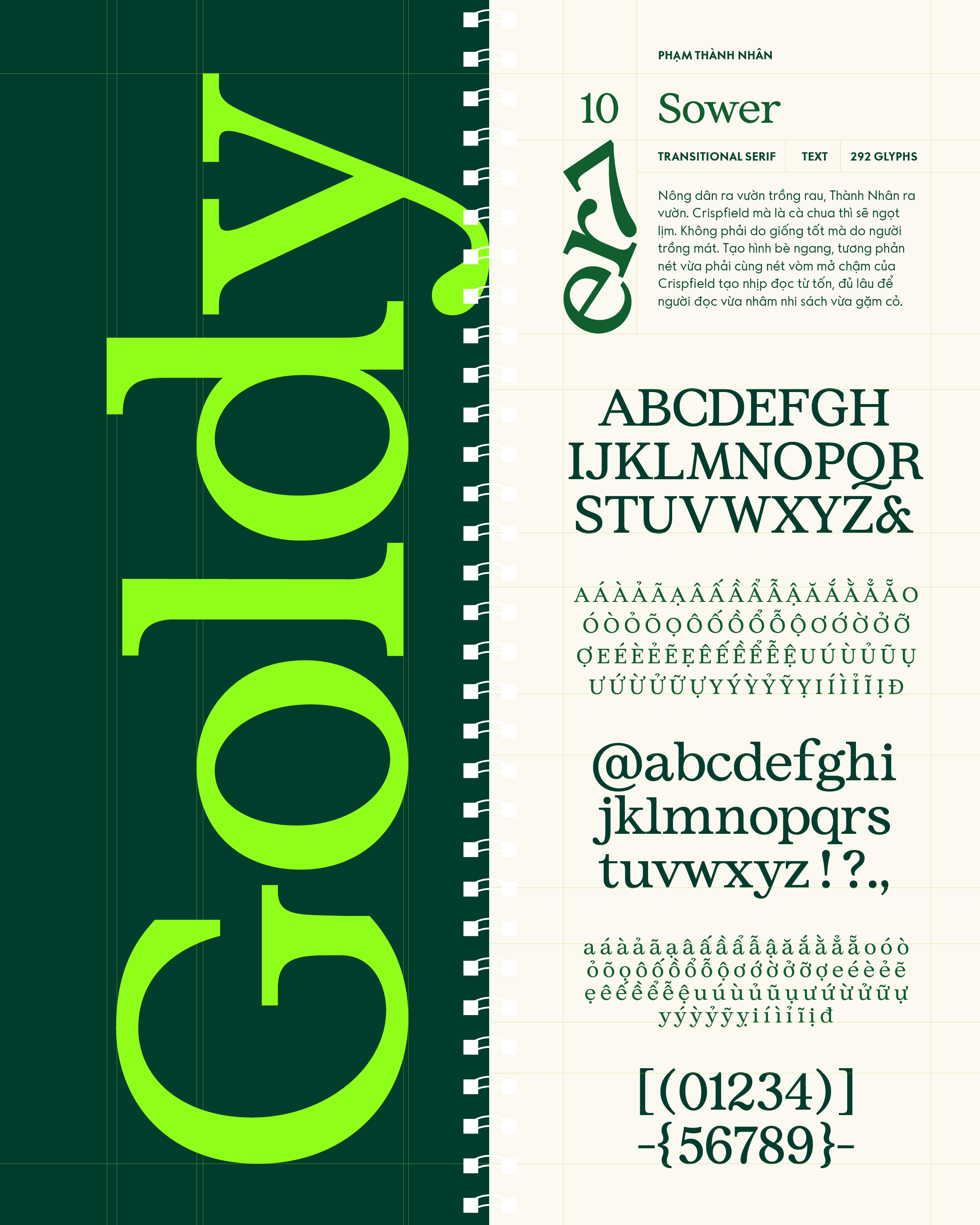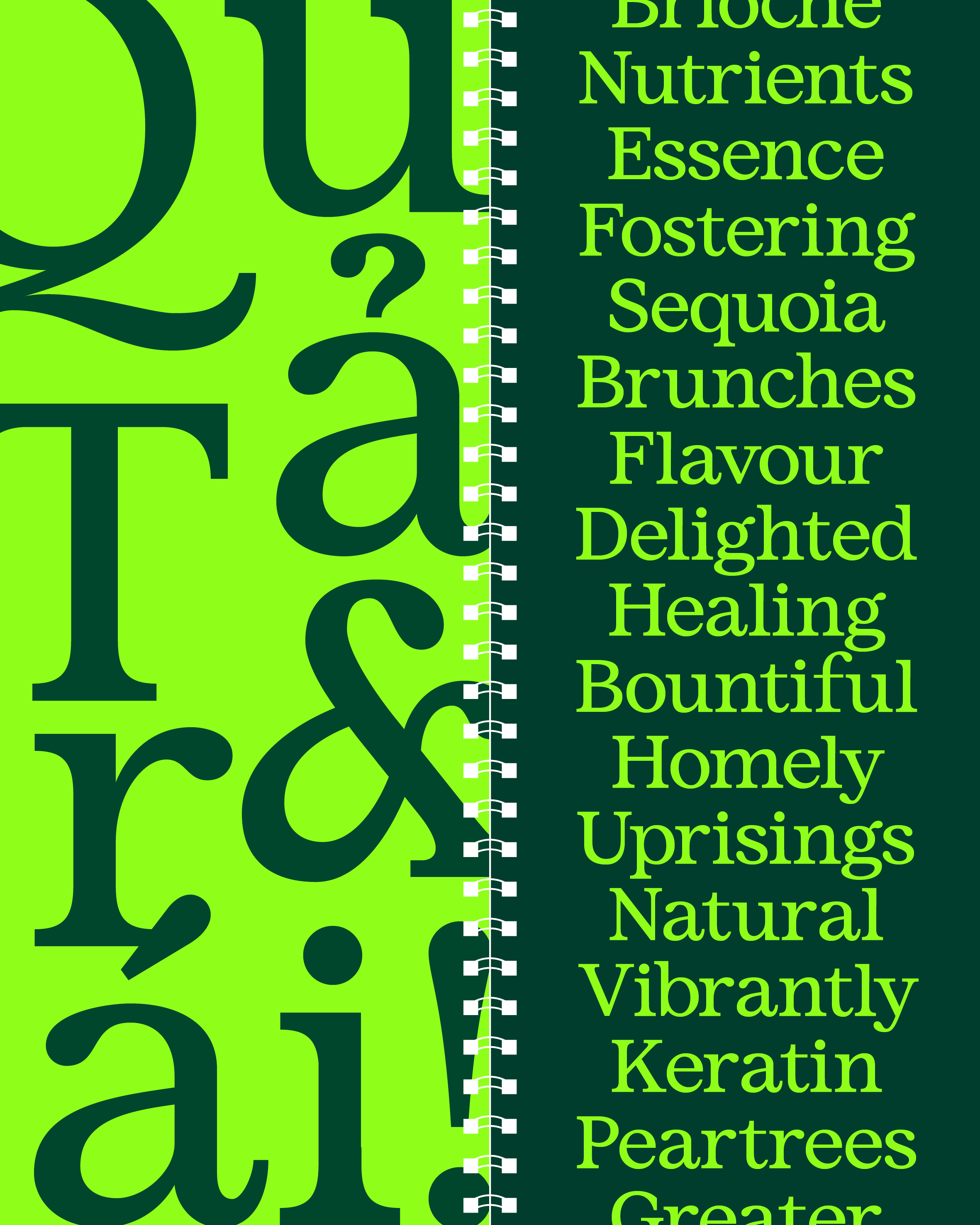
Sower
Về Sower: Nông dân ra vườn trồng rau, Thành Nhân ra vườn. Crispfield mà là cà chua thì sẽ ngọt lịm. Không phải do giống tốt mà do người trồng mát. Tạo hình bè ngang, tương phản nét vừa phải cùng nét vòm mở chậm của Crispfield tạo nhịp đọc từ tốn, đủ lâu để người đọc vừa nhâm nhi sách vừa gặm cỏ.
Transitional Serif
Text
Phạm Thành Nhân